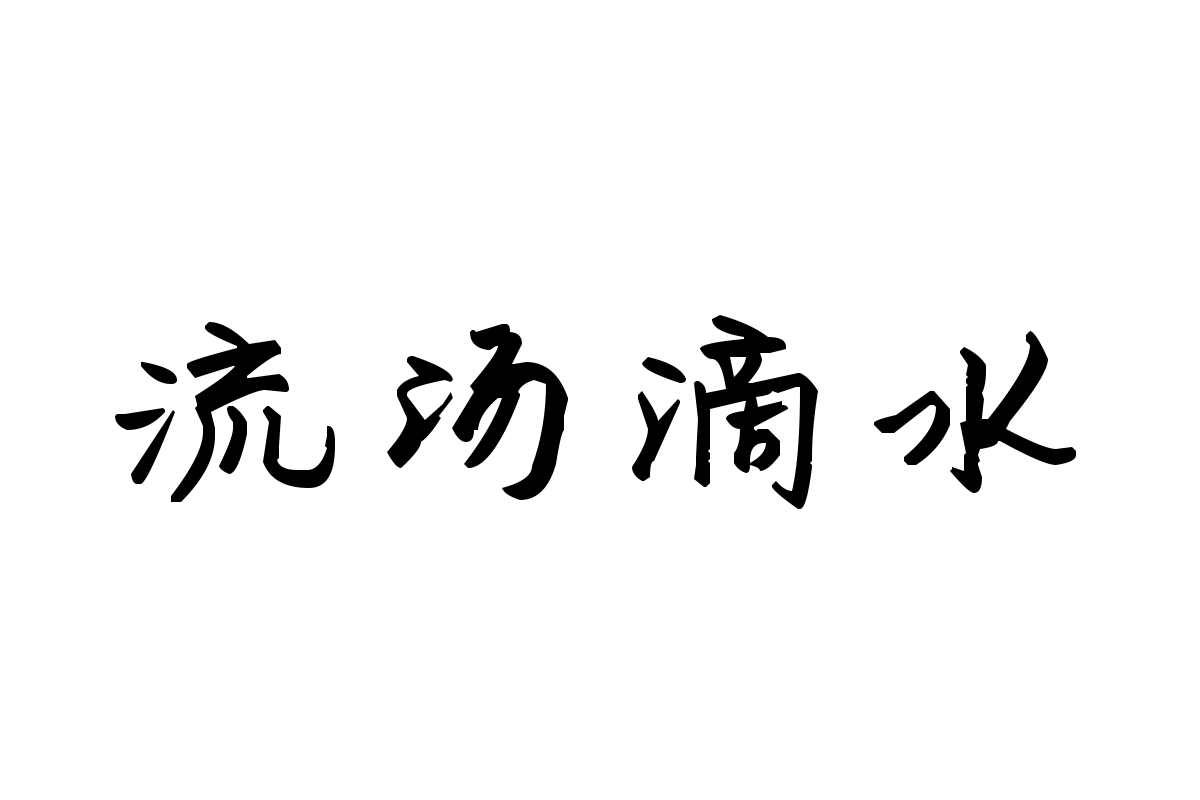
米开伊人若梦字体是一种具有独特魅力的中文手写艺术字体。它由著名书法家米开伊人创作,融合了中国传统书法的韵味和现代设计元素,展现出一种独特的美感。
米开伊人若梦字体的特点如下:
1. 线条流畅:该字体的笔画流畅自然,线条优美,给人一种优雅的感觉。
2. 结构紧凑:每个字符的结构紧凑,笔画分布均匀,使得整个字体看起来更加协调。
3. 风格独特:米开伊人若梦字体具有独特的个性,展现了作者对传统书法的深刻理解和个人风格。
4. 易于识别:该字体的字形清晰,易于辨识,适合用于各种场合,如印刷品、广告、包装等。
总之,米开伊人若梦字体是一种具有独特魅力的中文手写艺术字体,深受广大书法爱好者的喜爱。